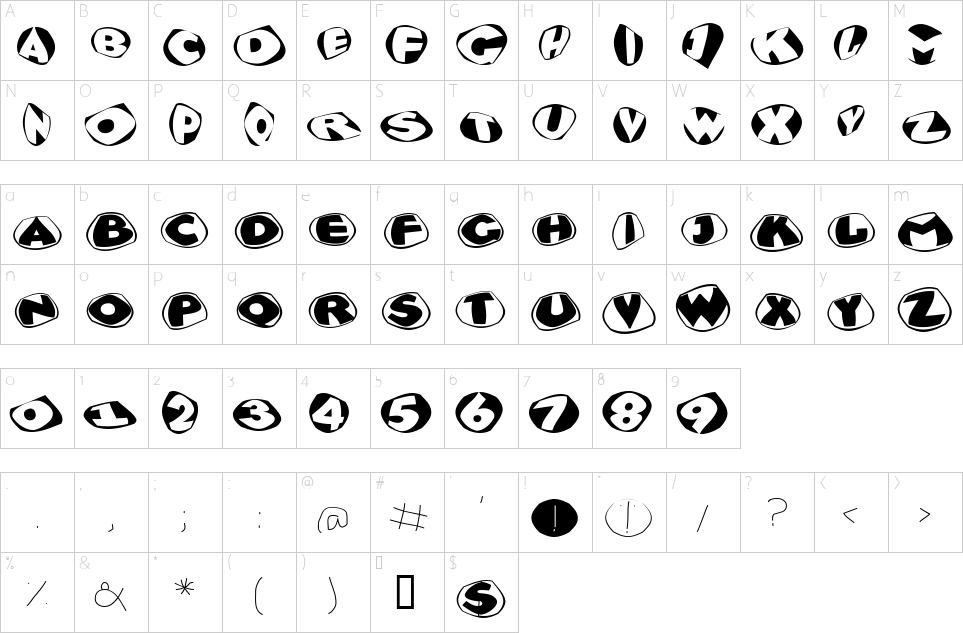
Descobrir uma nova fonte para seu próximo projeto pode ser tão gratificante quanto a descoberta de um novo tesouro. A Glyptographs Font, criada pelo talentoso Manfred Klein, é uma fonte gratuita que você pode instalar facilmente em seu sistema Windows ou Mac. Com uma aparência única e distintiva, esta fonte oferece uma escolha valiosa para aqueles que procuram uma opção moderna e elegante para seus documentos e projetos. Com apenas 1,328 instalações, a Glyptographs font já conquistou o coração de muitos criativos, incluindo você, que busca por uma fonte impecável sem ter que gastar um centavo. Instale a Glyptographs e experimente a beleza única desta fonte. Seja criativo e brinque com as diferentes aplicações que ela oferece. Você não terá nenhum motivo para se arrepender de ter escolhido esta fonte.